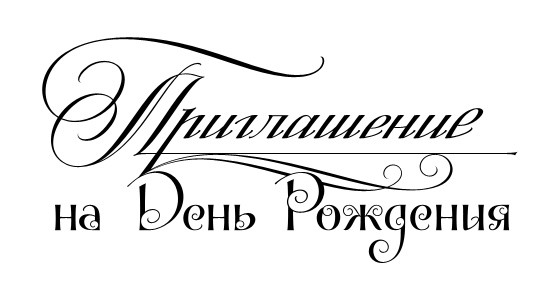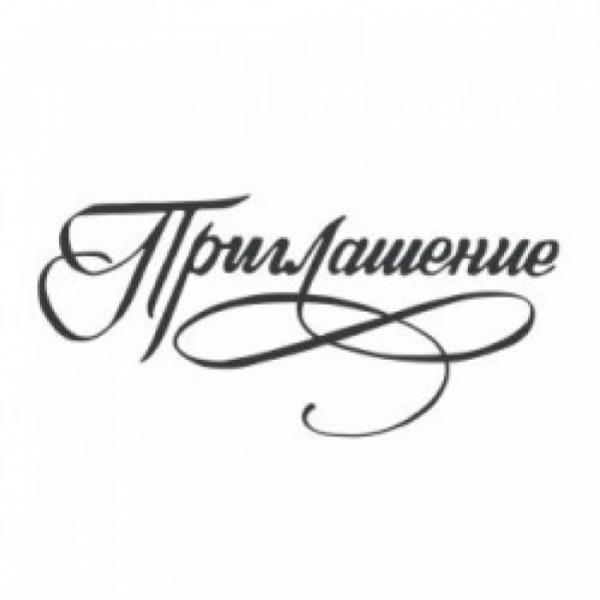
Текст для пригласительных на свадьбу,
Текст приглашения на свадьбу должен отражать настроение и характер торжества, выражать те эмоции, которые вы испытываете в преддверии самого важного дня вашей жизни события. Выбрать искренние и подходящие слова для каждого гостя вашей свадьбы – особый талант. Элегантное, наполненное особой любовью свадебное приглашение – это невероятное праздничное чувство, радостный аккорд, которым звучит долгожданная свадьба. Именно поэтому приглашения должны быть первоклассно выполнены, ведь они – визитная карточка торжества.
Текст свадебного приглашения в большинстве случаев указывает на общую стилистику торжества. Получая такую открытку, ваши гости сразу настраиваются на нужный лад. Вы можете использовать прикольный, оригинальный текст, чтобы привлечь внимание, или же сделать ставку на традиционность, подчеркнув изысканность и торжественность мероприятия. Хотите, чтобы ваше приглашение выгодно выделялось среди прочих и произвело нужное впечатление? Следуйте следующим правилам:
- Пригласительные на свадьбу должны обладать интересным и красивым дизайном. Только в таком случае гостю будет приятно держать открытку в руках и захочется сохранить ее на память.
- Персональные пригласительные, в которых имя адресата напечатано тем же шрифтом, что и вся открытка, а не написано от руки, выражают особое уважение к каждому гостю и указывают на высокий уровень подготовки.
- Дизайн открытки во многом определяется правильностью выбранного шрифта, расположением текста на листе, его цветом.
Грамотный подход в данном случае указывает на ваше безупречное чувство вкуса и делает прочтение пригласительного максимально приятным. - Важно точно определиться с тем, какой вы хотите видеть свою свадьбу. В зависимости от этого и стоит выбирать для пригласительных на свадьбу текст. Если вы сторонники классического подхода, то стиль текста должен быть официальным, если же вы решили справить свадьбу в кругу друзей, то в самый раз будут душевные слова. Оригинальная свадьба просто немыслима без приглашения с «изюминкой». Учтите, что шрифт и цвет печати текста в таком случае также должны соответствовать выбранному стилю.
- Художественные элементы разбавят «сухой» текст и придадут приглашениям завершенного вида.
Бесплатные Свадебные Шрифты — Приглашения На Свадьбу
Бесплатные свадебные шрифты могут помочь парам в планировании свадебных канцелярских принадлежностей. Бесплатные шрифты для вашей свадьбы просты в использовании, не жертвуя красотой и стилем. Несколько полезных советов помогут вам правильно использовать шрифты, чтобы приглашения на свадьбу выглядели так же профессионально, как и напечатанные на заказ.
Свадебные шрифты
Пары с ограниченным бюджетом могут сами сделать многие свадебные принадлежности, включая свадебные сувениры, свадебную фату или различные типы свадебных канцелярских принадлежностей. Бесплатные шрифты идеально подходят для:
- Сохраните карты свиданий
- пригласительные на свадьбу
- Программы свадебной церемонии
- Свадебный сайт
- Свадебные объявления
- Свадебные благодарственные записки
- Сделайте свои собственные свадебные приглашения
- Отличные свадебные подарки
- Уникальные свадебные украшения для торта
Использование одного и того же шрифта для разных типов свадебных канцелярских принадлежностей создаст элегантный, скоординированный вид, и им будет легче управлять, чем несколько шрифтов, стилей и дизайнов.
Что искать в шрифте
Выбрать свадебный шрифт сложнее, чем просто выбрать красивый. При выборе шрифта необходимо учитывать несколько факторов, в том числе:
- Набор символов : Если шрифт будет использоваться для нескольких целей, необходим полный набор символов, включая прописные и строчные буквы, цифры и знаки препинания. Специальные символы также могут быть желательны в зависимости от формулировки приглашения на свадьбу.
Eclectic Display Font Ideas
Хотите сделать заявление? Тогда дисплейный шрифт может быть просто билетом. Дисплейные шрифты также хороши, если ваша свадьба сильно зависит от темы, такой как ар-деко.
Шрифты для рассмотрения:
- Вон там
- Образец редкой птицы V
- Бортон
- Уоллингтон Про
- Мандарин
- Ореховый декор
- Хипстерский стиль